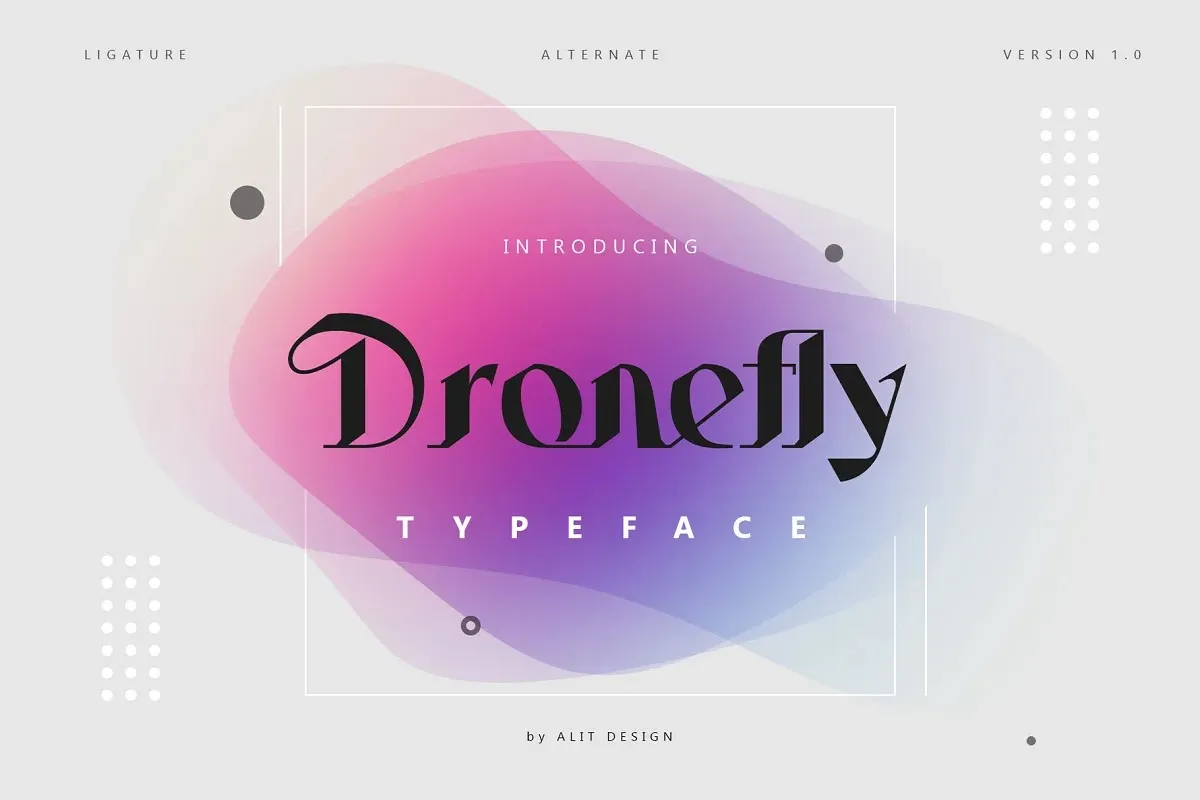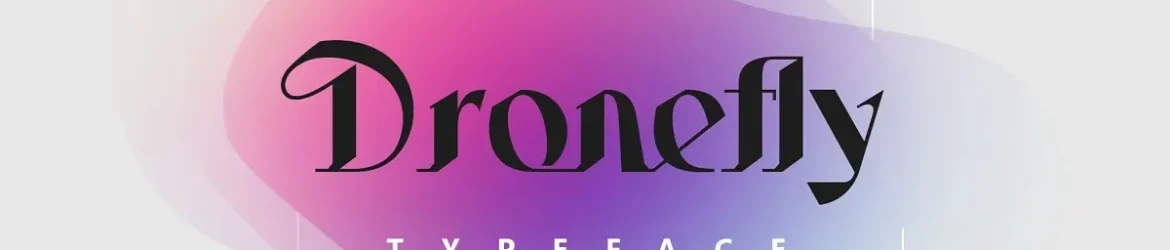
A Dronefly Font é uma escolha perfeita para quem busca estilo chamativo e individualidade nas suas criações digitais. Este tipo tipográfico de exibição apresenta linhas altas e fortes, junto com alternativas únicas que garantem um design distintivo e único. O resultado final impressiona visualmente, seja em cartazes, logotipos ou outros projetos visuais, tornando-os destaque na cena contemporânea. Desenvolvida com todo o carinho, essa fonte é uma verdadeira joia para designers que desejam dar um toque único e memorável a seus trabalhos. Ideal para expressar criatividade e personalização nos seus projetos de forma eficaz e imediata. A Dronefly Font é perfeita tanto para aqueles iniciantes no design digital quanto para profissionais experientes, proporcionando-lhes uma ferramenta poderosa para transformar seus ideais em realidade.